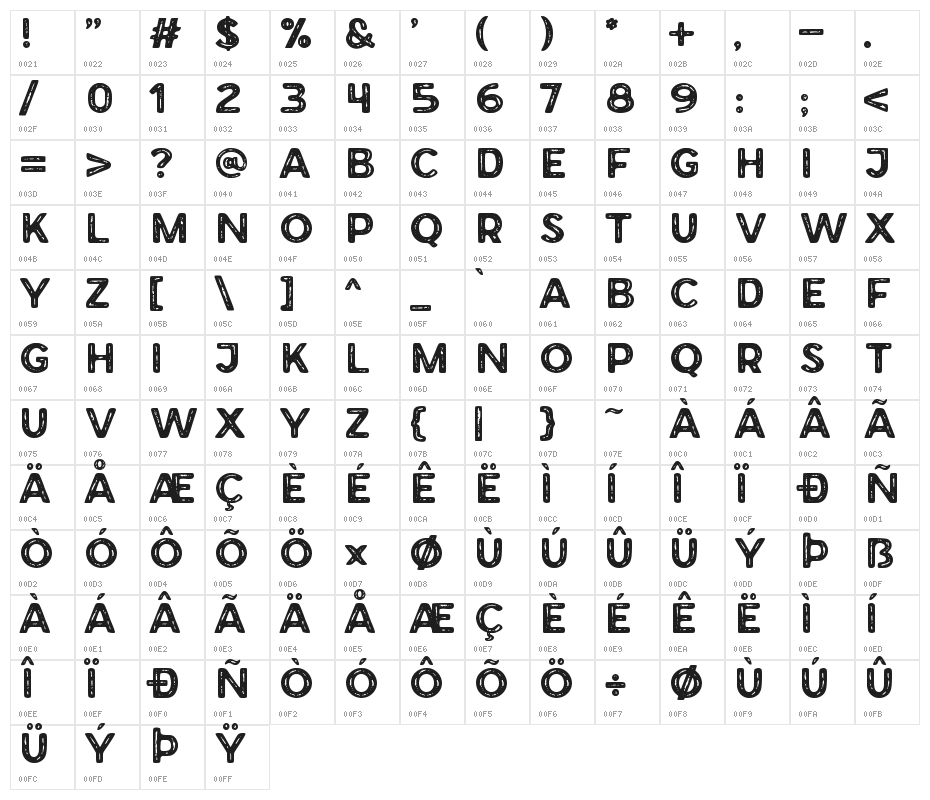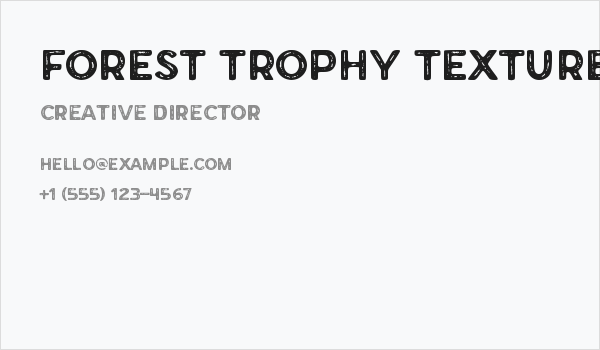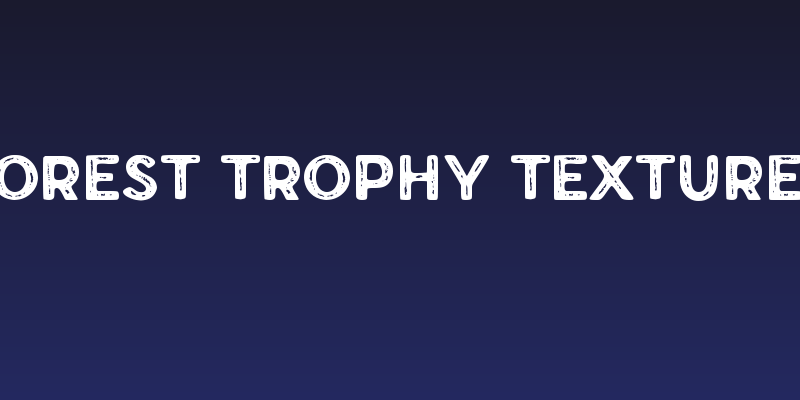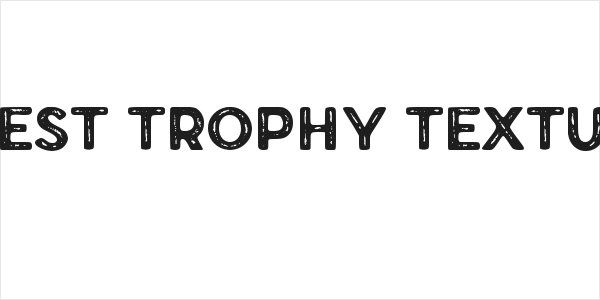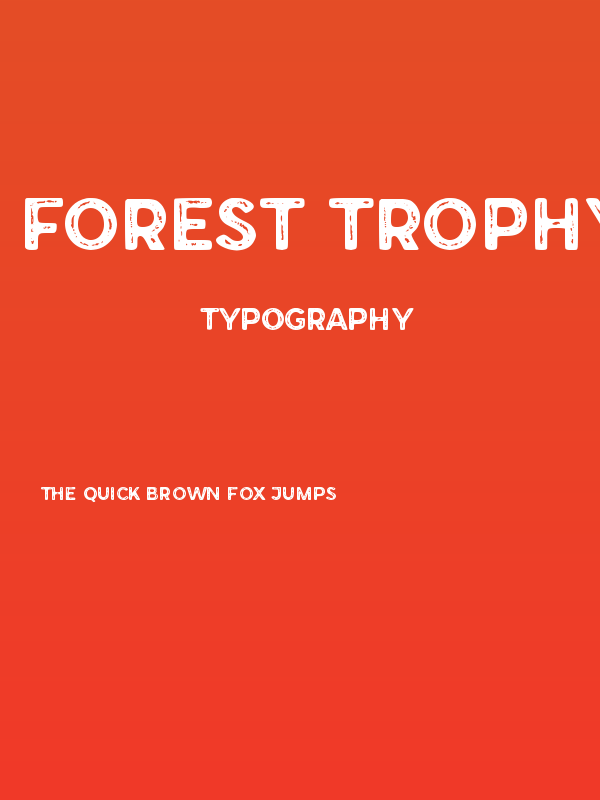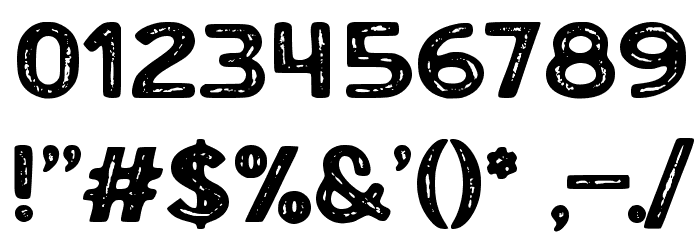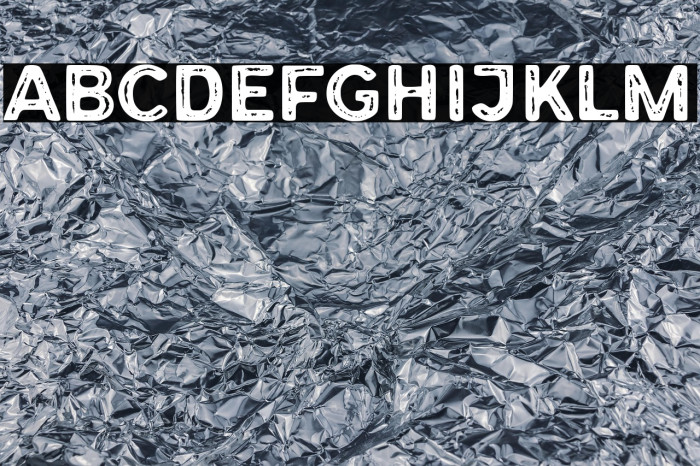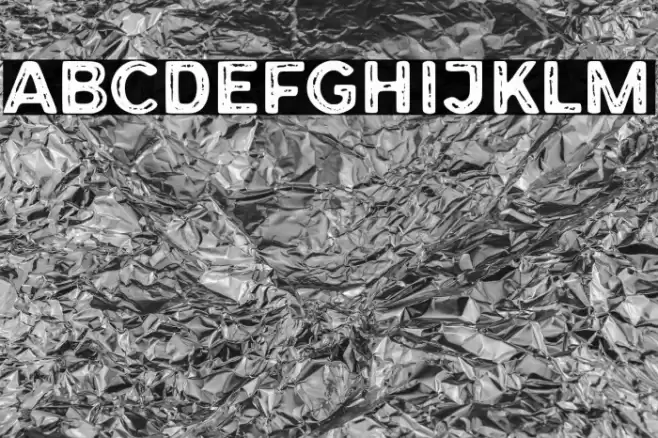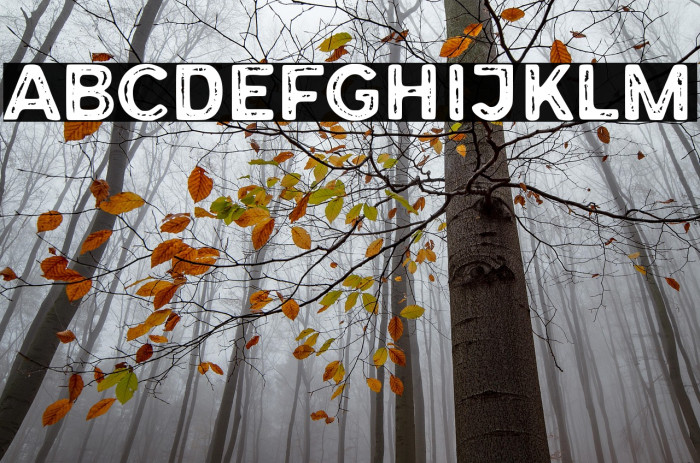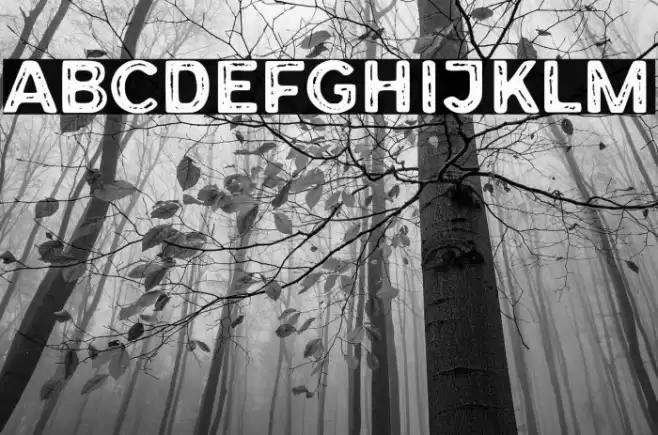
Forest Trophy Textured Font
✎ Thick
| Kategorien | Thick |
| Gesamtstil | Rustic, Handcrafted |
| Anwendungsfall | Logos, Headlines, Posters |
| Vorgeschlagene Projekte | Ideal for outdoor-themed branding, rustic wedding invitations, eco-friendly product packaging, and artisanal craft labels. |